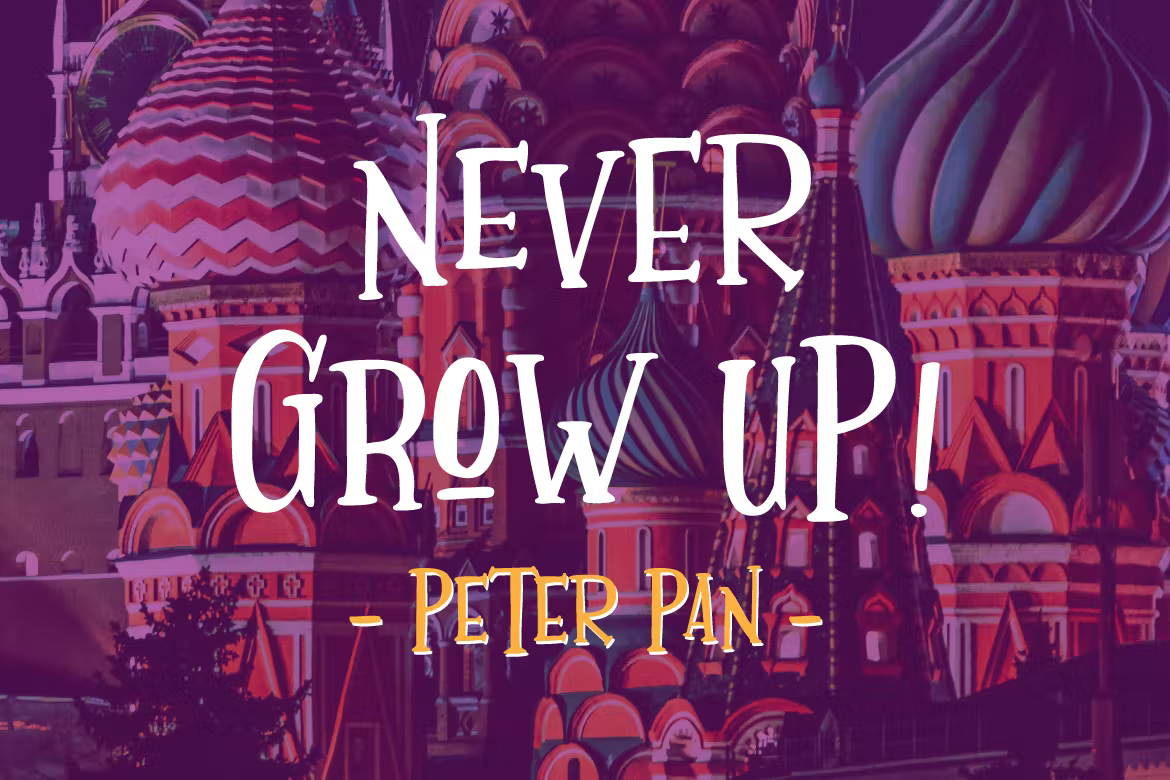
Whimsy Font
Whimsy est une police d’affichage fantastique/fantaisiste faite à la main. Il convient pour le titrage, l’affichage, la marque, l’artisanat, les citations, les t-shirts, les affiches, les emballages, les livres, les couvertures, les cartes, les invitations et plus encore.